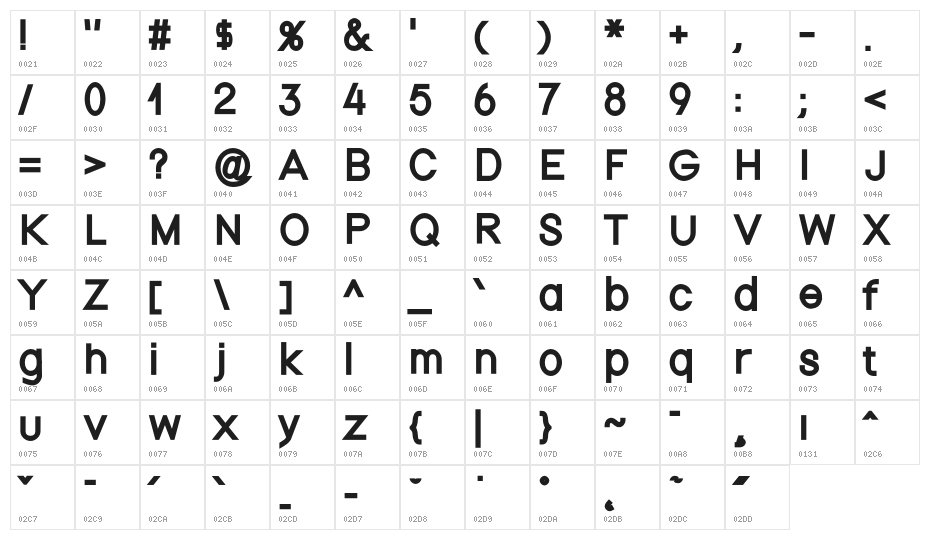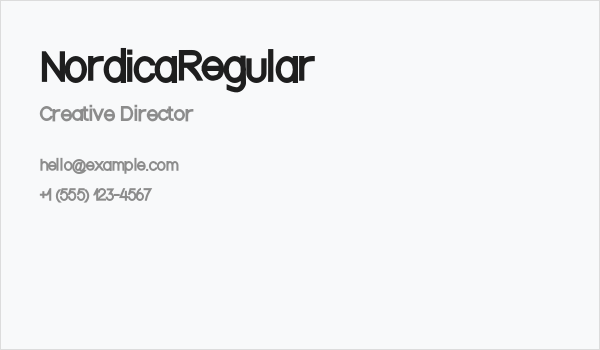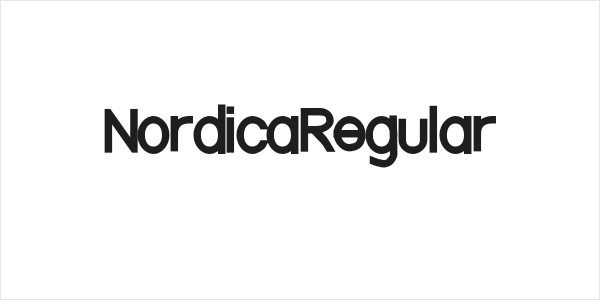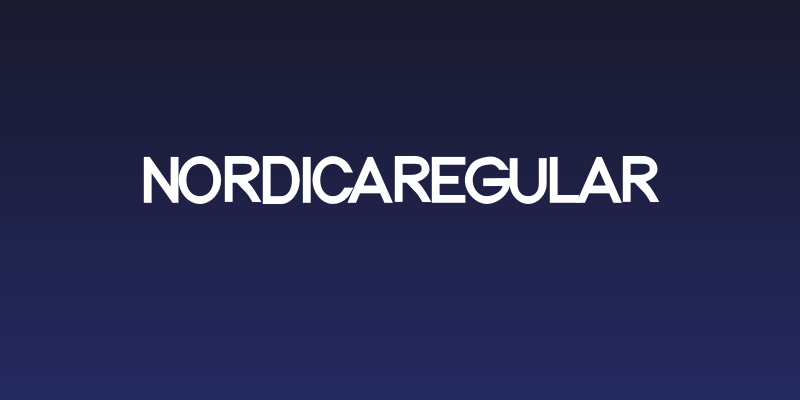
NordicaRegular Font
| 用途 | Headlines, Logos, Branding |
| おすすめプロジェクト | Ideal for branding, advertising, headlines, and digital media projects that require a strong, modern aesthetic. |